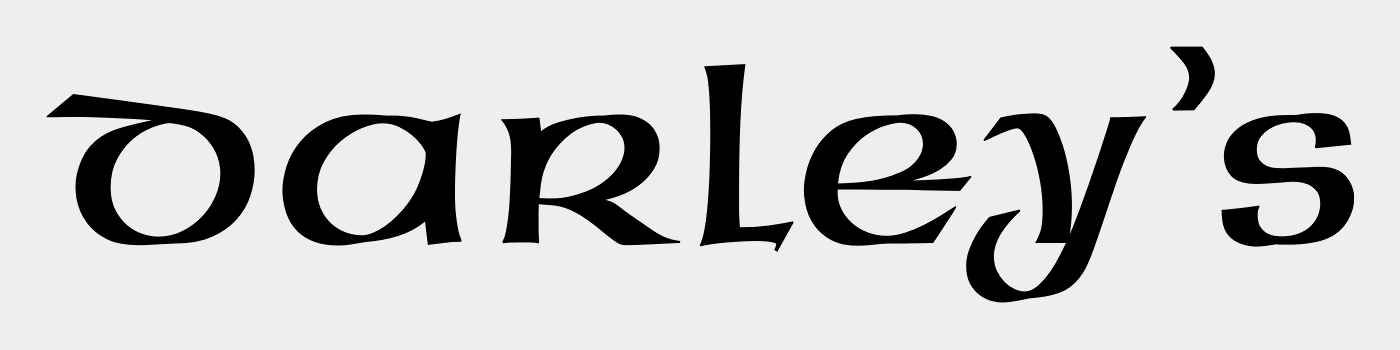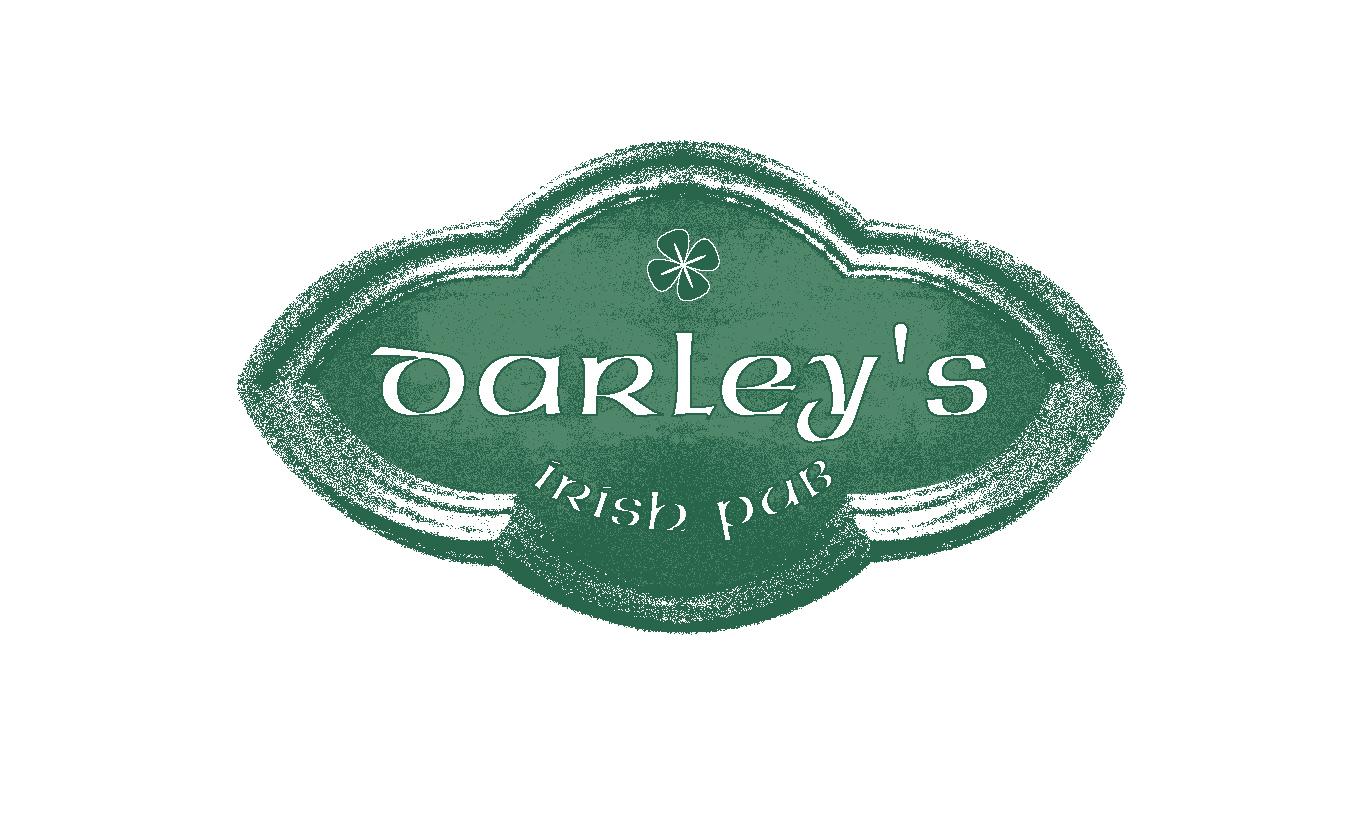
Suche die Schrift eines "Irish Pub" Logos
Könnt ihr erkennen welche Schrift in diesem Logo verwendet wurde? Ich denke jedenfalls, dass es eine Schrift ist, da der Buchstabe i gleich aussieht?!
Unzial typefaces consist of letter forms of the Capitalis Monumentalis and the majescule cursive. The origins of Unizial faces date back to the 5th century. The Neue Hammer Unziale was developed from the Hammer typeface, which was designed by Victor Hammer in 1921, cut by A. Schuricht and appeared with the font foundry Klingspor in 1923. In 1953, American Unizial was expanded to include some new figures, also designed by Hammer, and was rereleased by Klingspor with the name Neue Hammer Unziale. The forms are based on old scripts in books of antiquity and the early Middle Ages and the font is a new variation of a classic. Neue Hammer Unziale has been a favorite for certificates and diplomas and is recommended for headlines and shorter texts in a point size of 12 or larger. Quelle.